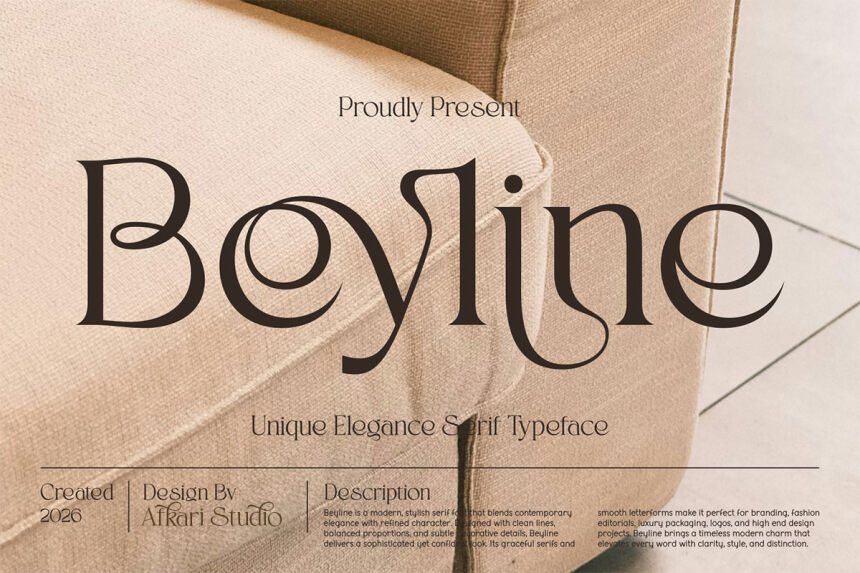
Beyline, do Afkari Studio, é uma fonte serifada gratuita de alto contraste com um toque fashion e levemente caligráfico. As letras combinam traços finos com curvas pronunciadas e junções longas e graciosas, conferindo à fonte um ar elegante, mas nada rígido.
Ela se adapta perfeitamente ao branding de beleza, embalagens de boutique, capas de revistas, papelaria de casamento e títulos que pedem um toque dramático. Como fonte gratuita, a Beyline sente-se em casa em manchetes curtas, logotipos e iniciais em estilo monograma, onde suas curvas amplas e alto contraste dão uma presença forte mesmo a poucas letras.